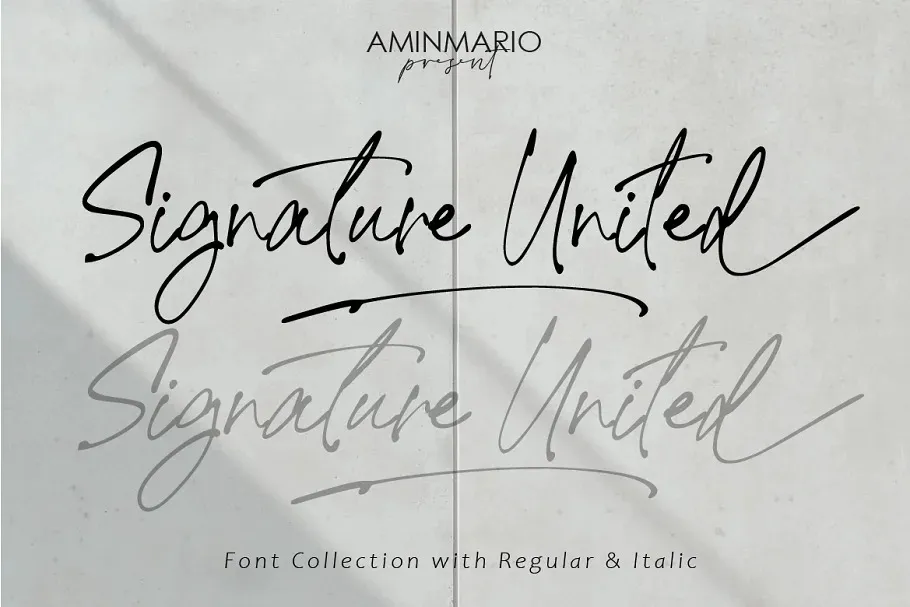
Signature United Script Font – Download Grátis
A fonte ‘Signature United Script Font’ oferece uma experiência visual envolvente que combina delicadeza com elegância. Este tipo de letra feita à mão exala sofisticação, destinada a projetos que buscam um toque natural e autêntico do mundo real. O designer da fonte, cuidadosamente incluiu elementos como letras minúsculas em estilo swash, ligatura e sublinhado, para criar uma reprodução tão próxima de uma escrita feita à mão quanto possível. Perfeita para qualquer projeto que exija um toque delicado do mundo da escrita livre. Esta font é perfeitamente projetada para dar um toque único aos textos em seu site ou aplicativo, seja em banners, headlines ou descrições de produto. E com sua delicadeza e elegância, certamente agradará tanto os clientes quanto quem está desenvolvendo o projeto. Seja por sua simplicidade ou complexidade, ‘Signature United Script Font’ é uma excelente escolha para aqueles buscando adicionar um toque único à página de download da fonte.